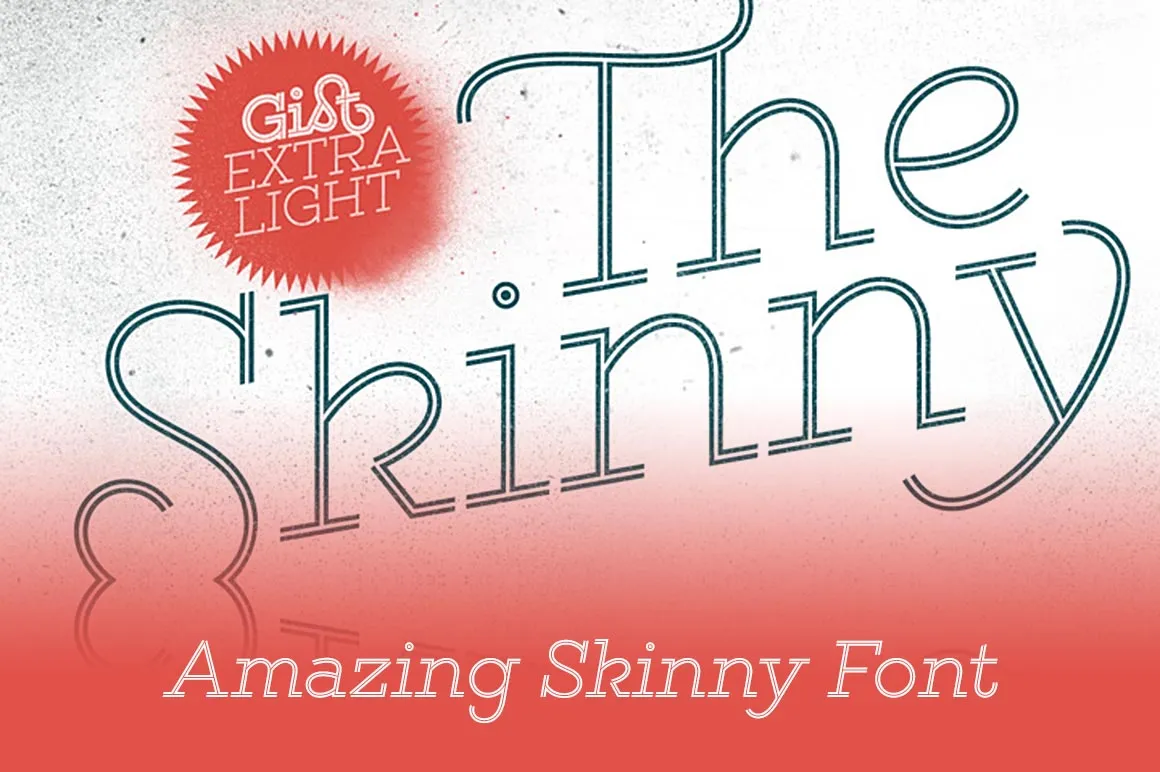
Gist Extra Light Font – Download Grátis
Esta fonte chamada ‘Gist Extra Light Font’ pertence à categoria Display Fonts criada pelo designer Hamilton. Com um toque de estilo retro na forma de suas letras, ela transmite uma sensação alegre e descontraída. Descarregue-a e desfrute da maneira como ela destaca seu design visual em qualquer projeto. Uma excelente fonte para dar um ar moderno e único a sua marca ou conteúdo digital. É perfeita para headlines, títulos de página ou qualquer lugar onde você deseja destacar o design e a personalidade do seu trabalho.